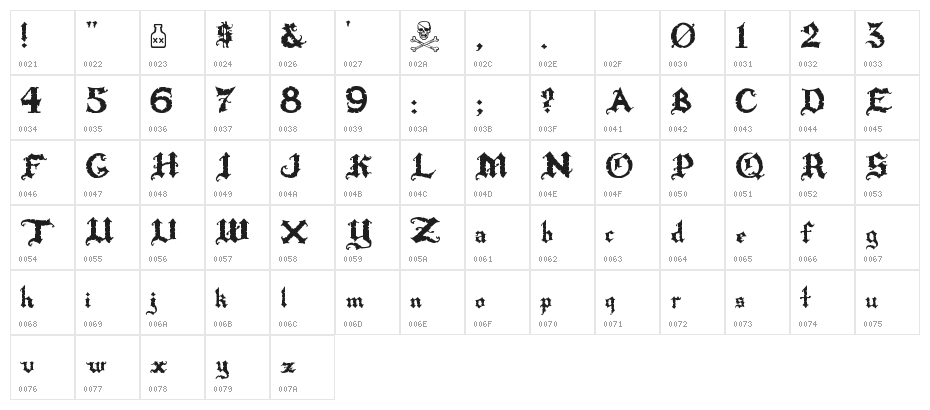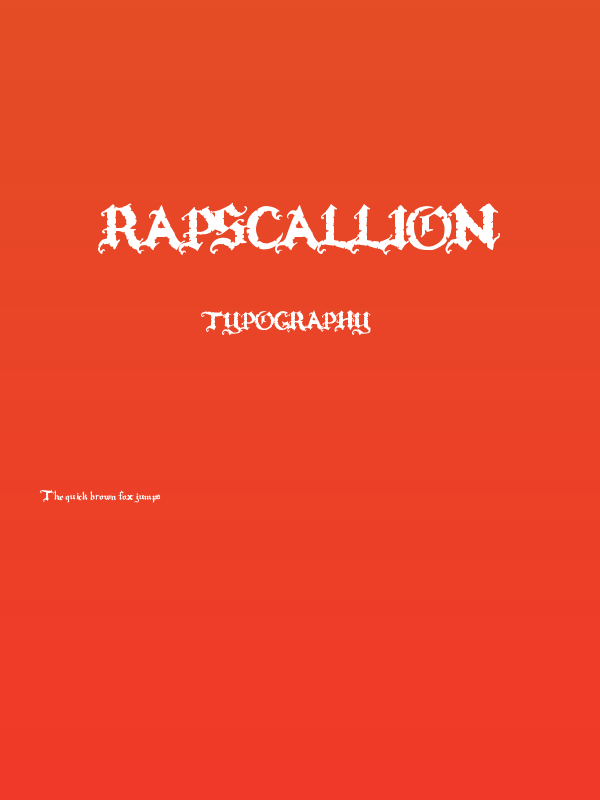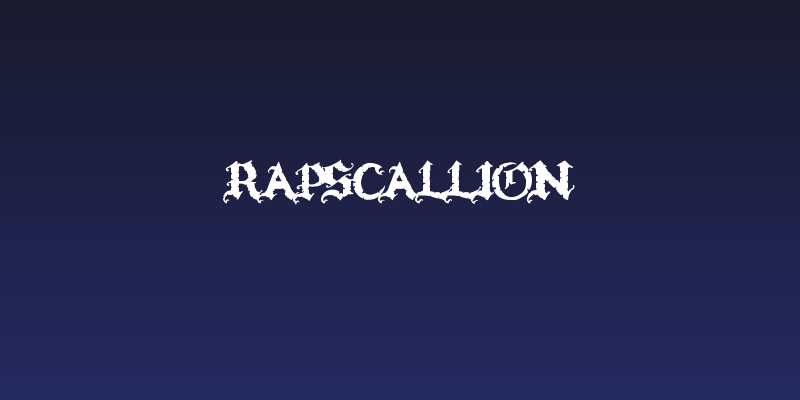
Rapscallion Font
✎ Gothic
| Caso d'uso | Logos, Posters, Themed Events |
| Progetti proposti | Ideal for pirate-themed designs, Halloween events, edgy posters, and adventurous branding. |